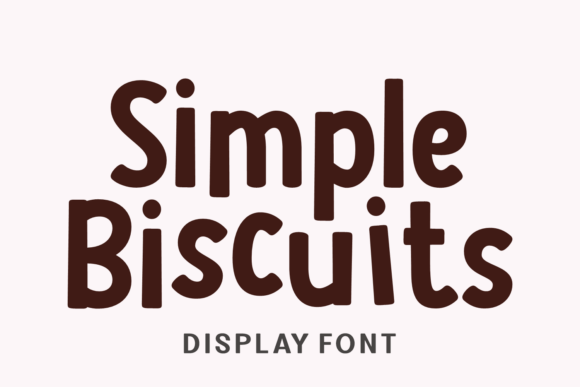
Simple Biscuits
Het vinden van de juiste ontwerpelementen kan lastig zijn, maar Simple Biscuits biedt een uitzonderlijke collectie die uw werk direct naar een hoger niveau tilt.
Of u nu POD-producten (Print on Demand), huwelijksuitnodigingen of afbeeldingen voor sociale media maakt, Simple Biscuits is een ideale keuze.